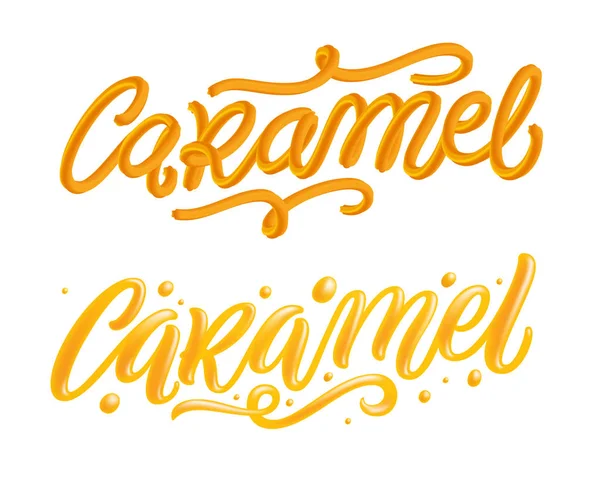
Шрифтовый дизайн в рекламе — Теория рекламы
Креативную и эффективную рекламу можно создавать только (и я это подчеркиваю!) с помощью шрифтовой игры.
Как? — об этом статья. В основе анализа — семиотический подход. Напомню: семиотика — вполне прикладная дисциплина о знаках, каждый из которых представлят собой коммуникативную (и креативную!) стратегию.
Шрифтовая игра — особый аспект, не относящийся к смыслу слов или грамматическим правилам их написания. Нас интересует сам шрифт: его цвет, размер, необычное расположение букв, разнообразные сочетания с картинкой и тому подобное.
Как наука о знаковых системах, семиотика состоит из четырех основных разделов, или уровней: алфабетики, семантики, синтактики и прагматики. И на каждом из этих уровней можно отследить, проанализировать, а значит, и применить опыт шрифтового креатива, или шрифтовой игры.
С точки зрения алфабетики
В алфабетике, разделе семиотики о первичных, буквенных элементах и
структурах языка, главное — параметры шрифта. На поле алфабетики отлично
играют такие оппозиции, как кирилический/латинский, серийный /
несерийный, печатный / рисованный, вариативный / инвариантный и т.
Несколько примеров. В рекламе звукозаписывающей студии одни и те же слова brille (рис.1) и jeans (рис.2) ошрифтованы десятками разных, непохожих друг на друга способов, что, безусловно — знак того, что здешние специалисты — настоящие гуру аранжировки.
Использование шрифтов в рекламе студии звукозаписи рис. 1
Часто знаковость шрифта связана с его размером и цветом. Так, в рекламе звуковой техники значения «интерпретированы» с помощью «комиксовых» начертаний и цвета. В первой рекламе (рис. 3) эти приемы воплощают идею «выпуклости», а во второй (рис.4) — идею «расчлененности» значения.
Использование шрифтов в рекламе звуковой техники LG рис. 3
Использование шрифтов в рекламе звуковой техники LG рис. 4
С помощью шрифтовых характеристик можно отразить широкий спектр интонационных и смысловых характеристик. Например, переход на черный шрифт буквально подчеркивает особую важность выделенного сообщения (рис.
5). И наоборот, в рекламе презервативов (рис. 6) «размытый» заголовок намекает на тайну и волнение.